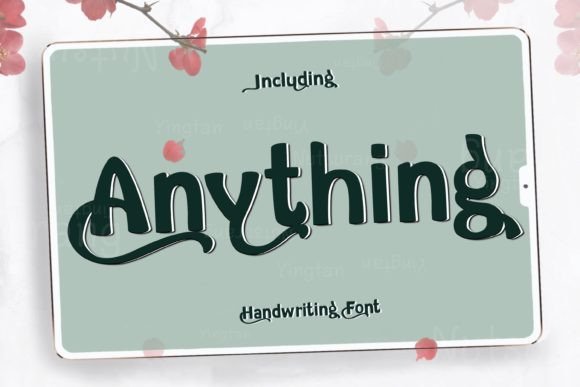
Anything
Anything์™€ ๊ฐ™์€ ๊ณ ํ’ˆ์งˆ ์ž์‚ฐ์„ ์ฐพ๊ณ  ์žˆ๋‹ค๋ฉด ์ด ํ”„๋ฆฌ๋ฏธ์—„ ํŒจํ‚ค์ง€๋Š” ์ฐฝ์˜์ ์ธ ํ”„๋กœ์ ํŠธ๋ฅผ ์œ„ํ•œ ํ™˜์ƒ์ ์ธ ์„ ํƒ์ž…๋‹ˆ๋‹ค.
์ •๋ฐ€ํ•˜๊ฒŒ ์ œ์ž‘๋œ Anything๋Š” ๊น”๋”ํ•œ ๋ฒกํ„ฐ, ๋ถ€๋“œ๋Ÿฌ์šด ํƒ€์ดํฌ๊ทธ๋ž˜ํ”ผ ๋ฐ ์•ˆ์‹ฌํ•  ์ˆ˜ ์žˆ๋Š” ์ƒ์—…์šฉ ๋ผ์ด์„ ์Šค๋ฅผ ์ œ๊ณตํ•ฉ๋‹ˆ๋‹ค.